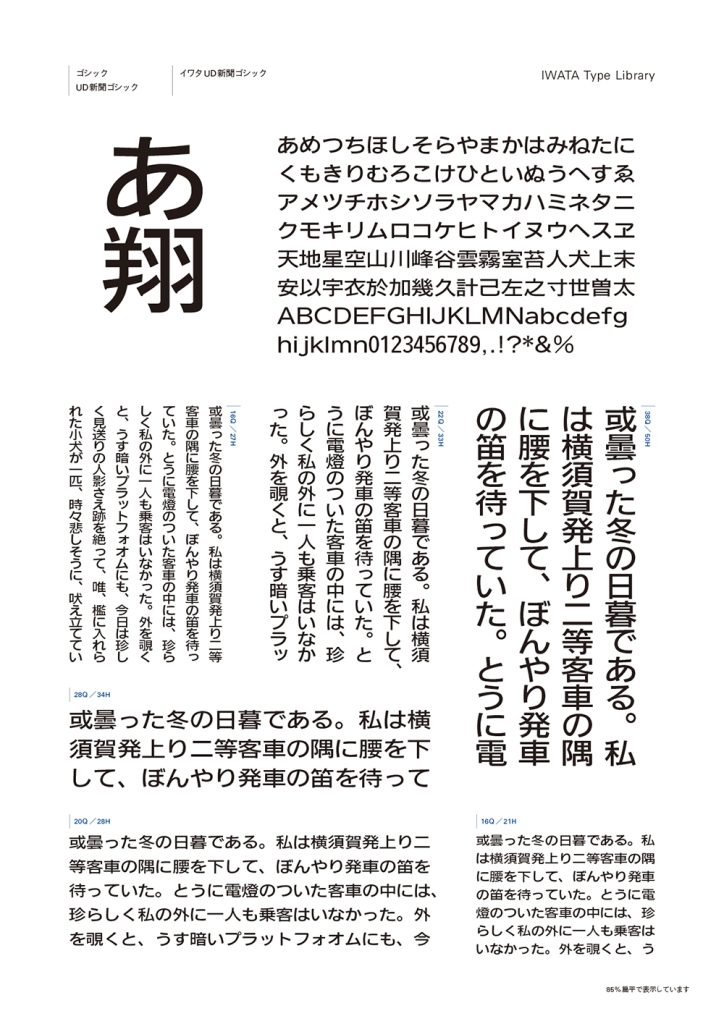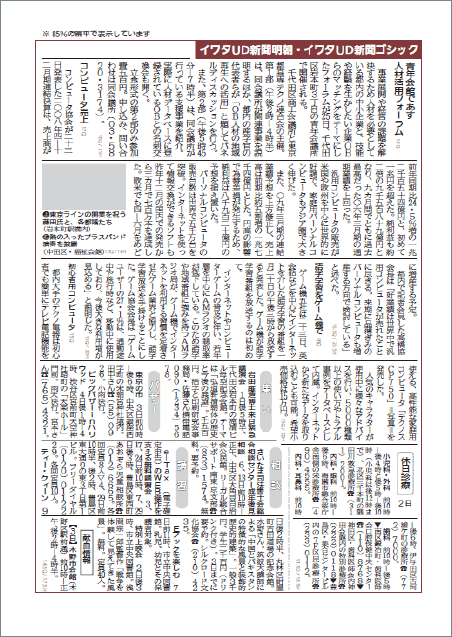
UD新聞ゴシック
イワタUD新聞ゴシック
情報量よりも読みやすさが求められる、時代の要請に対応した、“次世代の新聞ゴシック体”です。信濃新聞社の協力により輪転機印刷テストを実施し、新聞印刷に最適化するように調整を施しています。視認性の良さと長文での読みやすさを兼ね備え、新聞本文だけでなく、情報を明瞭に伝えるあらゆる印刷物に適した書体です。
開発の背景
戦後間もない1951 年、新聞紙面は1 ページ15 段、1 段15 文字制がスタートしましたが、人口の高齢化に伴い、新聞紙面では大文字化のニーズが急速に高まりました。そのため2008 年には多くの紙面の組み体裁が変更され、1 ページ15 段の枠から脱却し、12 段にして文字を大きくする新聞社も登場しました。しかし、本文サイズを単純に拡大するだけでは、読みやすく美しい紙面を実現することはできません。拡大された文字サイズにふさわしく、ユニバーサルデザイン(UD)の視点からも改良された新聞書体が求められるようになりました。このような環境の中で誕生した「UD 新聞明朝」と同コンセプトで、誰にでも読みやすい新聞ゴシック体も開発するに至りました。
書体デザインのポイント
UD の思想に基づき、誰もが見やすく読みやすい文字であると同時に、文字の品位、平体での使用、広めのふところといった新聞書体の歴史的なプロポーションは引き継ぐなど、美しい紙面構成のための様々な工夫がされています。
※「イワタ新聞中ゴシック体」と「イワタUD 新聞ゴシック体」を比較しています(扁平率はどちらも85%)